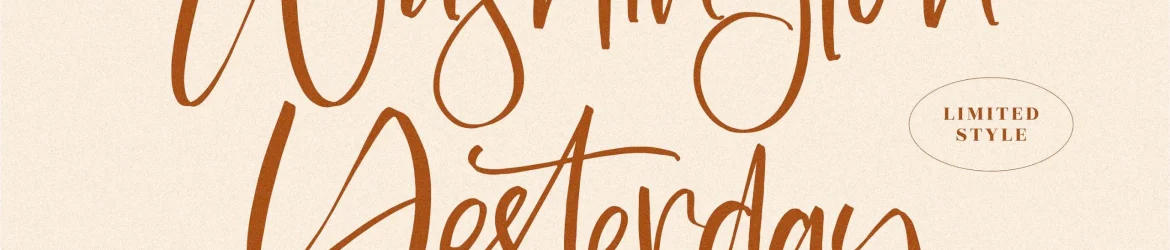
Washington Yesterday Font – Download Grátis
Esta é uma fonte escrita a mão perfeita para projetos variados, desde selos até caixas de embalagem personalizadas. Perfeitamente adequada para criações como logos, etiquetas, pacotes de produtos e materiais promocionais. A fonte também se adapta bem aos designers de móveis de luxo, arte para camisas ou sacolas, capas de livros e cartões de visita. Seja qual for o projeto que exige um toque de escrita a mão, este fonte é perfeito. Além disso, pode ser usada em carteirinhas de endereços, convites para eventos especiais ou até mesmo nas criações fotográficas. O designer perspectype criou esta fonte elegante e única, oferecendo um toque pessoal que tornará seu projeto ainda mais especial. Com certeza não há nada melhor do que uma fonte escrita a mão perfeitamente combinada para criar um design único, envolvente e de alta qualidade.